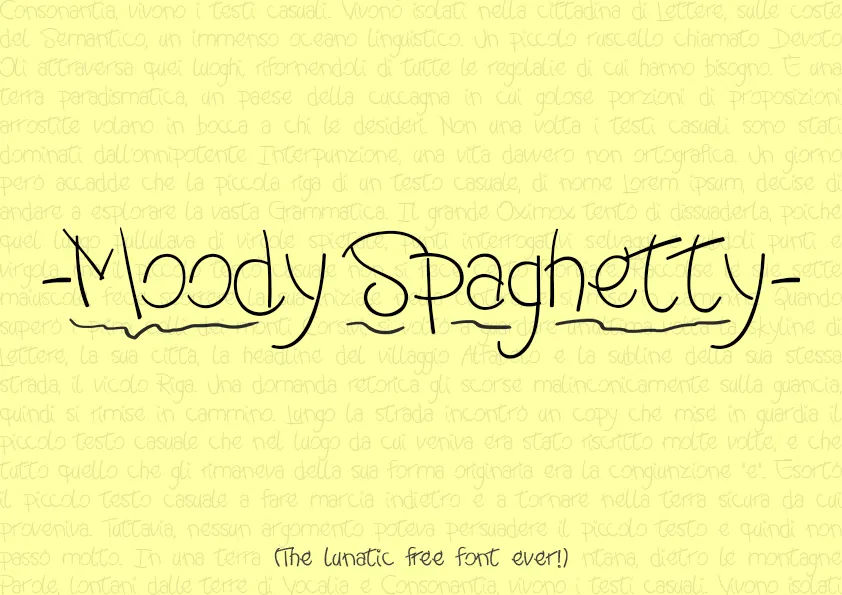
Moody Spaghetty Font
Aqui está uma descrição em português para a página de download da fonte ‘Moody Spaghetty Font’, mantendo os requisitos fornecidos: O designer Hamilton trouxe um ar descontraído e autêntico à sua ‘Moody Spaghetty Font’ com suas letras delicadas e fluidas. Esta fonte, categorizada como handwritten, é ideal para aqueles que desejam adicionar uma sensação única ao seu trabalho gráfico. Com linhas levemente onduladas e traços bem marcados, a ‘Moody Spaghetty Font’ cria um efeito de letra escrita à mão em estilo spaghetti, garantindo sempre um toque autêntico e divertido. A fonte foi criada por Camilla Bertoni, uma artista talentosa que sabe equilibrar os detalhes mais sutis com a essência da sua arte. Ao escolher ‘Moody Spaghetty Font’, você se juntará à muitos designers que valorizam tanto o aspecto visual quanto a mensagem transmitida em suas criações. Esta fonte, embora seja designada para escrita casual e criativa, também é uma ótima opção para uso em aplicações gráficas digitais, permitindo-lhe criar um toque pessoal que se destaca no meio de outras. A ‘Moody Spaghetty Font’ não apenas tornará seu trabalho mais interessante, mas também fornecerá aos seus usuários uma fonte única e divertida para explorar. Sinta-se à vontade para usar a sua criatividade ao escrever com esta fonte e seja parte da comunidade de designers que enriquecem suas criações convidando os olhos do mundo.